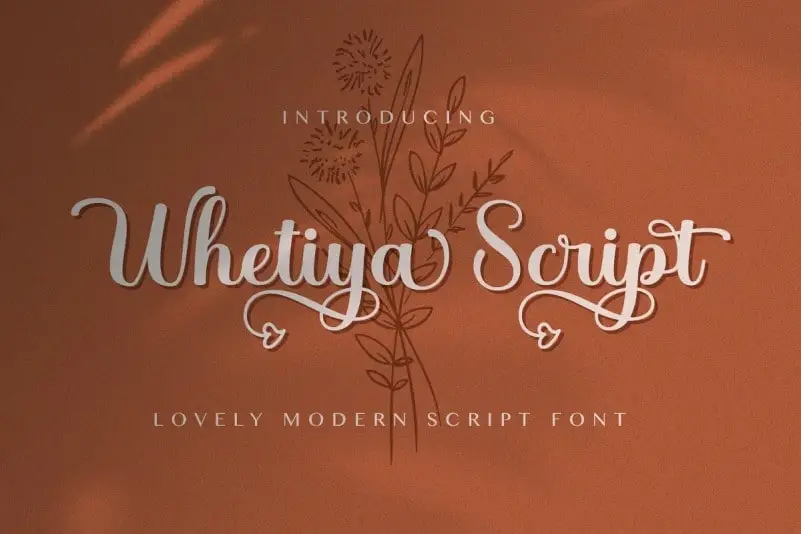
Whetiya Calligraphy Font – Download Grátis
A Whetiya Calligraphy Font é uma elegante tipografia criada pela StringLabs com diferentes swashes deslumbrantes, meticulosamente projetados para se tornar a fonte de desejo número um. Mantém seu estilo clássico e influência da calligrafia enquanto mantêm-se contemporâneos e frescos. Quem ama essa fonte, pode transformar seus projetos no nível mais alto. Ideal para quem busca uma fonte que combina sofisticação com modernidade, a Whetiya Calligraphy Font é perfeita para aquelas criações de design que desejam se destacar na cena criativa. Desfrute da versatilidade dessa elegante tipografia e reinvente seu trabalho de arte digital e impressões, tornando-o ainda mais especial com cada uso.